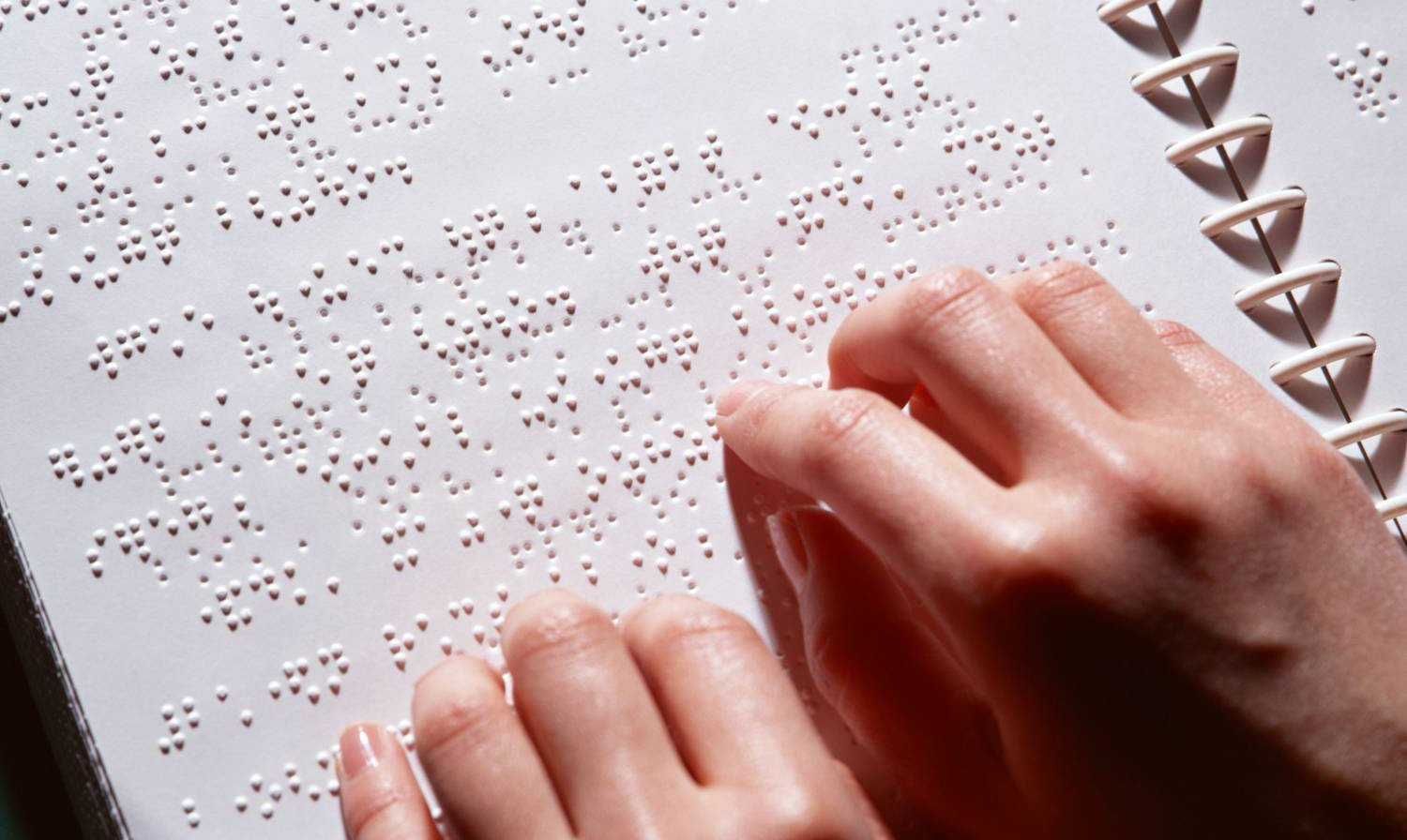
Завдяки такому алфавіту люди із вадами зору можуть читати, писати та отримувати важливі знання. Азбука являє собою набір музичних, математичних символів та букв алфавіту, кожна з яких утворена із випуклих крапок.
Для людей з вадами зору життя в замкнутому просторі створює низку проблем в аспекті незалежності та ізоляції. Насамперед для тих, хто покладається на використання дотику, щоб передати свої потреби та отримати доступ до інформації.
Пандемія COVID-19 показала, наскільки важливо виробляти необхідну інформацію у доступних форматах, зокрема шрифтом Брайля та аудіоформатах. Якщо цього не робити, то люди з вадами зору матимуть значно вищий ризик заразитися.
Всесвітній день азбуки Брайля відзначається, аби підвищити поінформованість про її значення. Вона є одним із засобів спілкування для повної реалізації прав незрячих та людей з вадами зору.
Використання азбуки Брайля забезпечує передачу важливої ​​інформації. Крім того, є проявом професіоналізму, незалежності та рівності.
Що таке абетка Брайля
Абетка Брайля є тактильним представленням символів за допомогою шести точок, які дозволяють передати всі літери, цифри й навіть музичні, математичні та наукові символи. Вона використовується незрячими й людьми з вадами зору для читання.
• Крім того, у 2021 році школярі з порушенням зору вже складали зовнішнє незалежне оцінювання з використанням завдань, які надрукували шрифтом Брайля. Тестування провели під час додаткової сесії.